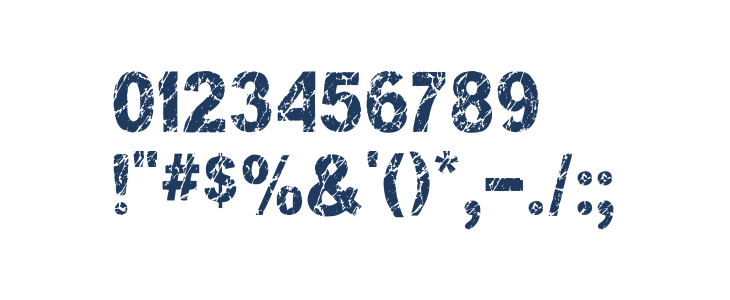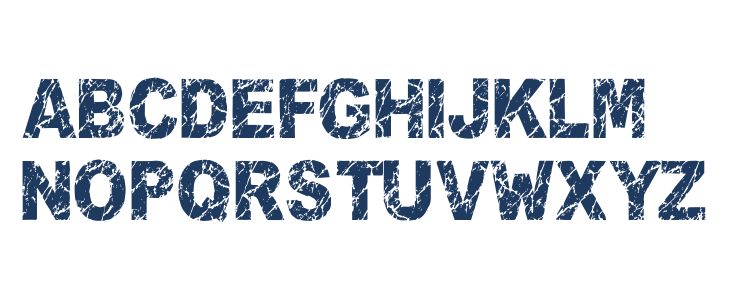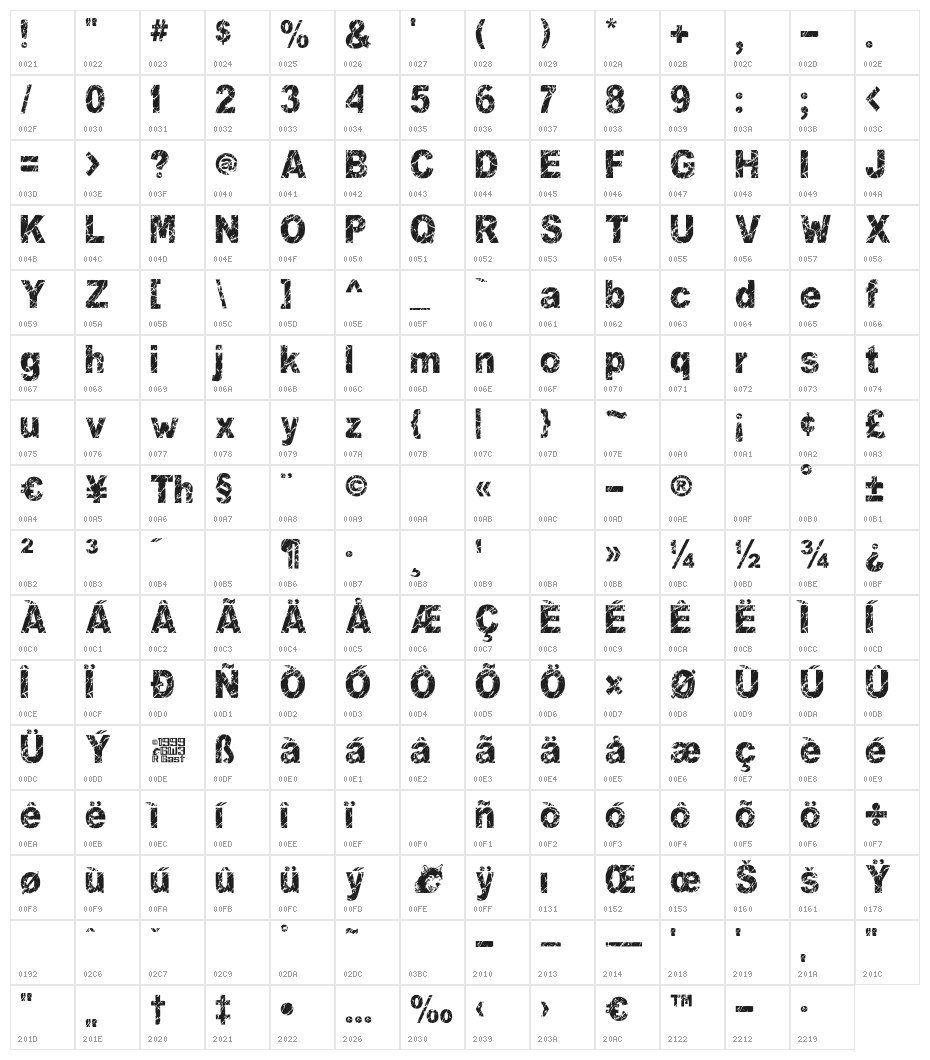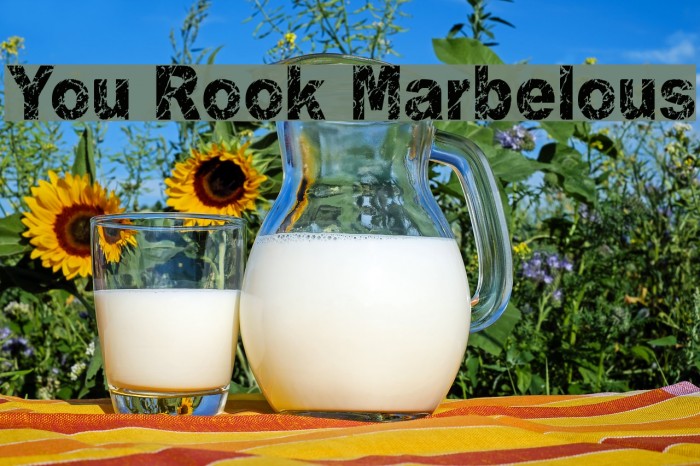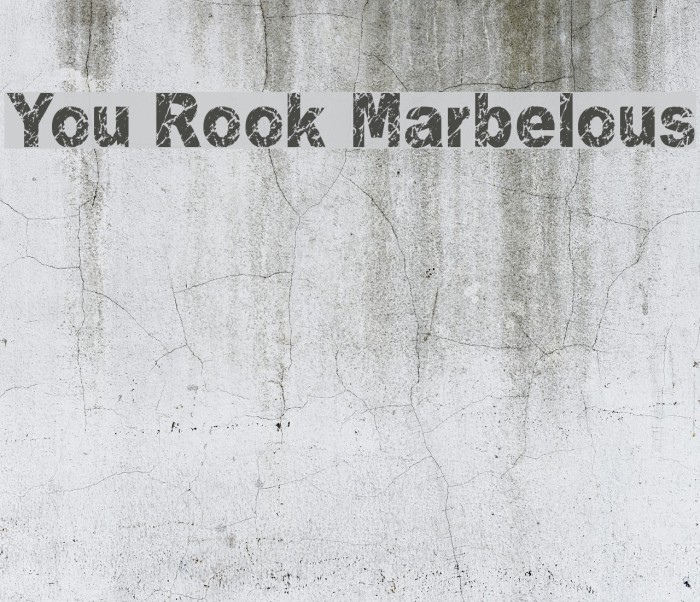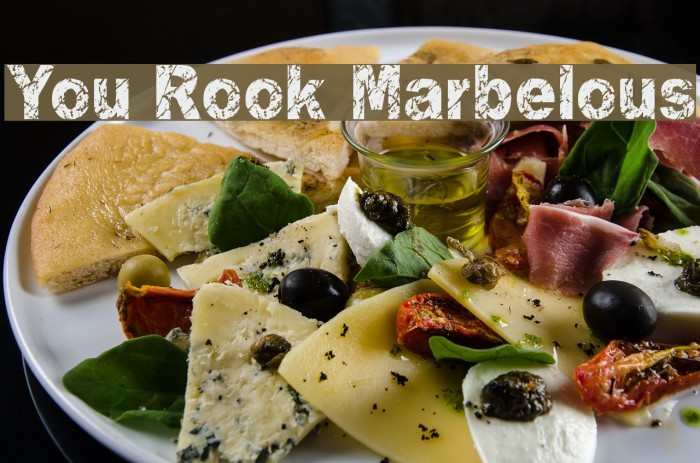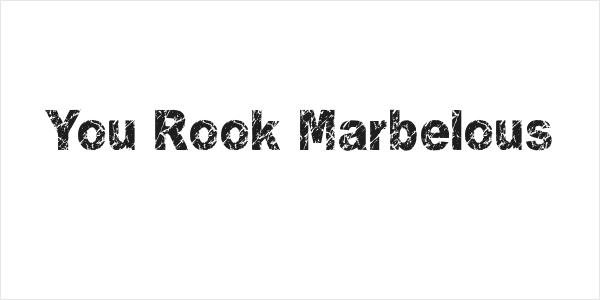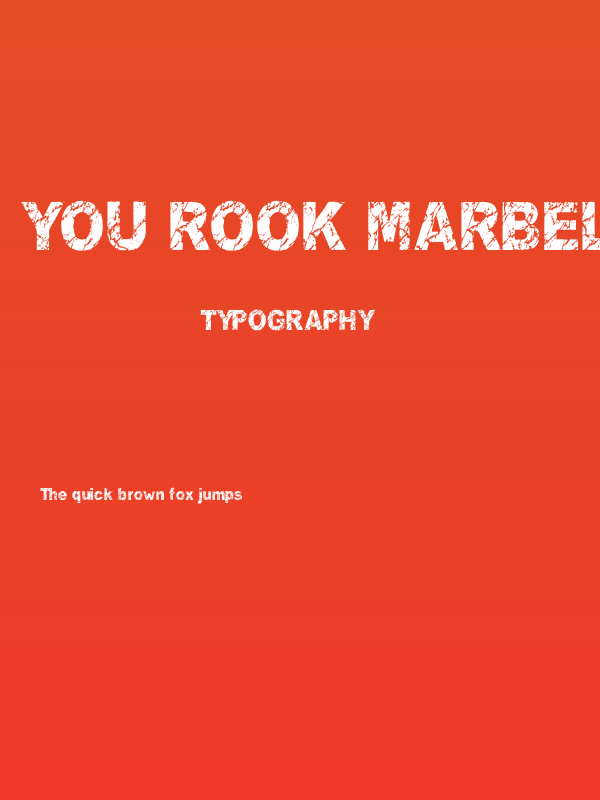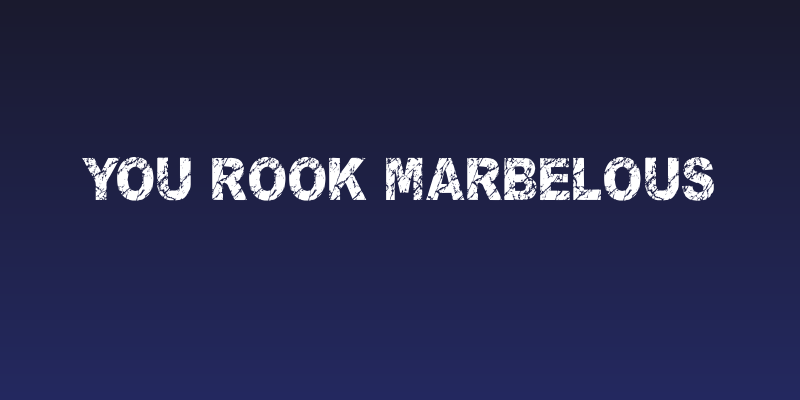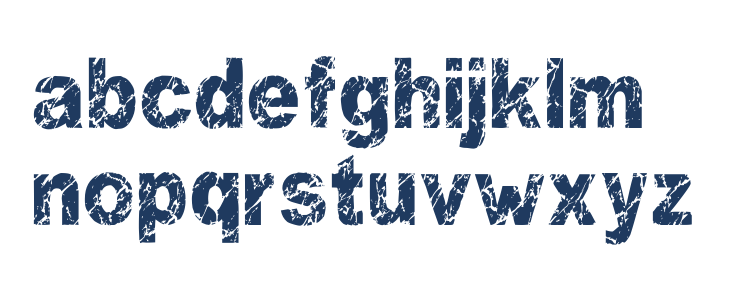
You Rook Marbelous Font
| Categorie | Broken |
| Stile generale | Grunge, Vintage |
| Progetti proposti | Ideal for posters, album covers, branding for edgy products, and any design needing a vintage or grunge aesthetic. |